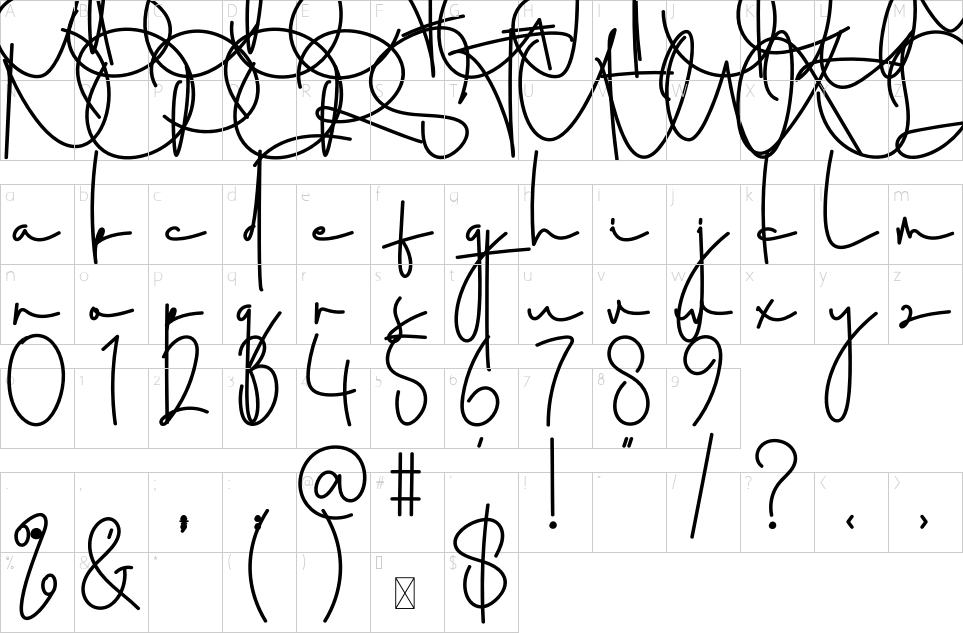
Descubra a beleza e a simplicidade de Santa Picture Font, uma elegante fonte grátis disponível para download para Windows e Mac. Desenvolvida por scratchones, esta fonte possui um design encantador que se destaca entre as muitas opções de fontes disponíveis. Com uma arquitetura minimalista e uma tipografia cuidadosamente projetada, Santa Picture Font é ideal para criar designs gráficos, como cartões de aniversário, calendários e até mesmo cartazes de natal. Se você procura uma fonte para tornar seu design mais atraente e personalizado, esta é uma ótima escolha. Com seu design agradável e fácil de usar, a Santa Picture Font é uma fonte perfeita para aqueles que buscam um desafio visual sem comprometer a simplicidade. Em 2023, já foram baixadas 336 vezes esta fonte gratuita, evidenciando seu valor e relevância no mercado dos recursos gráficos. Seja você um profissional ou um amante da design, Santa Picture Font é uma fonte que você não pode deixar de experimentar.